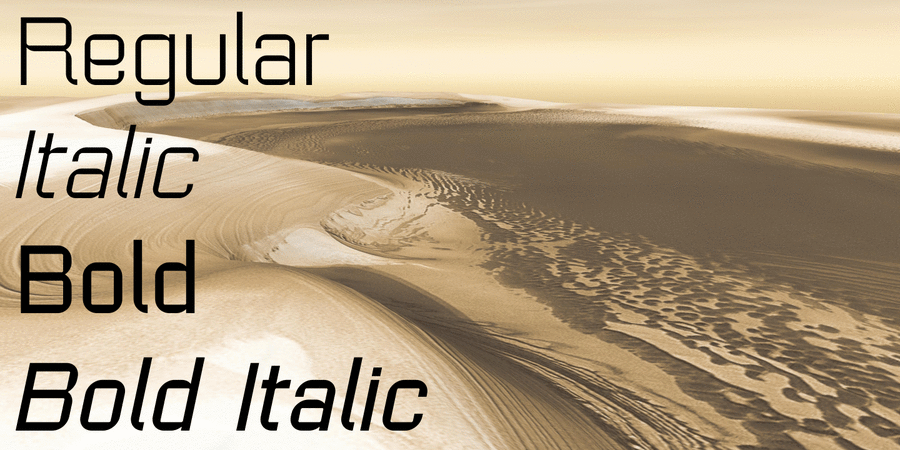
Опис гарнітури GeomanticusШрифт Геомантикус – геометрический модульный гротеск с техногенным характером. Разработан в студии 2D Typo Лукьяном Турецким в 2012 году.
Асоціації з сімейством шрифтів GeomanticusОсобистість і характер гарнітури:
космічний, лаконічний, твердий, статичний, точний, рівний, стійкий, автоматичний, штучний, холодний, машинний, інженерний, прямий, індустріальний, сучасний, техногенний, прямокутний, футуристичний, комп'ютерний, електронний, урбаністичний, байдужий, креслярський, експериментальний, залізний, сталевий, надійний, впевнений, сильний, кінематографічний
техніка, прилад, фантастика, конструктор, креслення, інженер, автоматика, робот, електроніка, комп'ютер, космос, наука, проводка, інновації, гаджет, девайс, урбаністика, гра, айтішник, IT, айті, технології, андроїд, залізо, астрономія, інструмент, ракета, супутник, ремонт, кіно, кіберспорт, комп'ютерна гра Гарнітура асоціюється з віком: